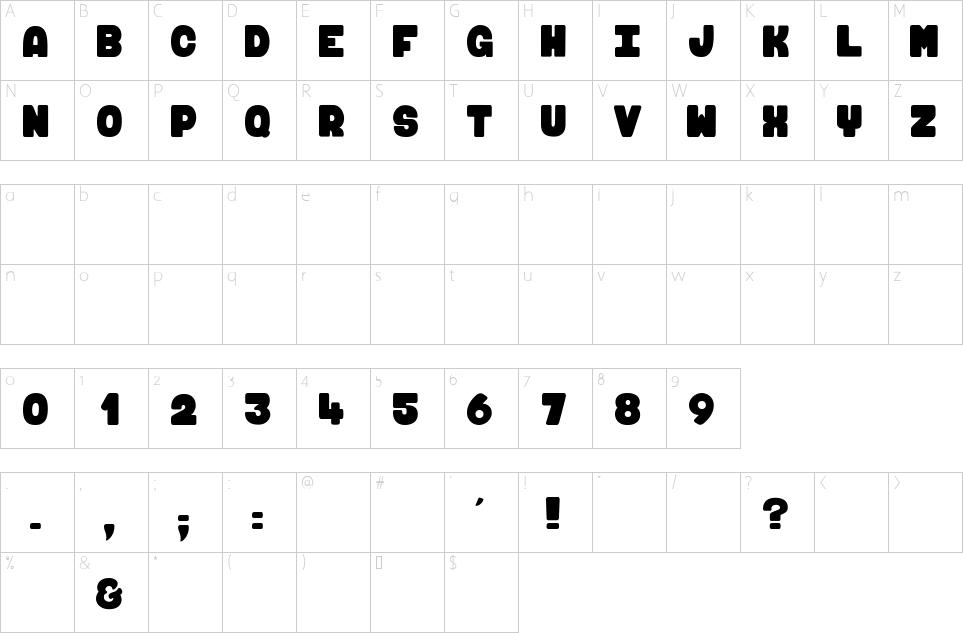
A fonte Maki Fugu é uma escolha agradável para qualquer designer gráfico. Desenvolvida por dcoxy, ela tem se destacado entre os usuários devido à sua elegância e facilidade de uso. Descrita como um tipo de fonte futurista e minimalista, Maki Fugu oferece uma aparência moderna e moderna que se adapta bem a uma variedade de projetos, desde pequenos elementos de design até grandes banners de website. Atualmente, a fonte já foi baixada mais de 11.974 vezes, mostrando a popularidade e qualidade de Maki Fugu. Seja você um estudante de design ou um profissional, Maki Fugu é uma excelente escolha para personalizar seu próximo projeto.